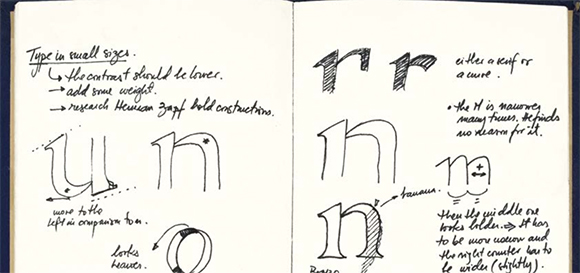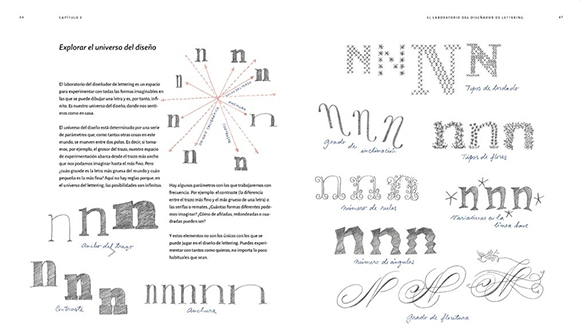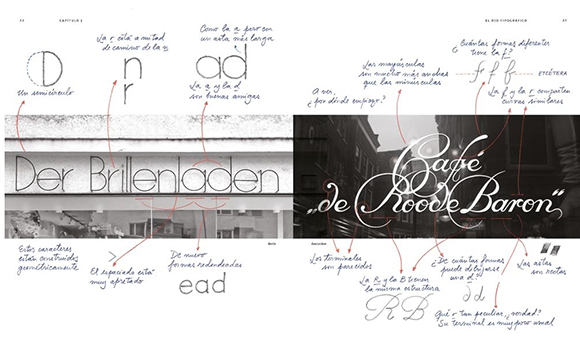
El lettering en su vocablo inglés, o rotulación en español, fue una herramienta importante de la gráfica aplicada que vivió su periodo de esplendor hasta mediados del siglo pasado en el que poco a poco fue sustituido por el vinilo y las tipografías digitales. Pero como al final “todo vuelve”, de un tiempo a esta parte todos los que nos interesamos por la letra y sus formas hemos comprobado el auge que ha experimentado la caligrafía y la rotulación tanto como medio de expresión personal como de desempeño profesional.
Y un buen ejemplo de ello es el libro que hoy comentamos: Los grandes secretos del lettering de la diseñadora e ilustradora Martina Flor. Tengo que reconocer que se trata de un manual ambicioso ya que abarca desde los principios y técnicas en los que se basa este arte hasta el aprovechamiento comercial y profesional del mismo con un capítulo dedicado a la digitalización de la obra para su reproducción comercial y otro en el que la autora ilustra a los lectores sobre la planificación del proyecto y al trato con el posible cliente.
No cabe duda de que adquirir destreza dibujando letras no es tarea fácil por eso me parecen muy interesantes los capítulos destinados a educar el «ojo tipográfico», el que nos muestra los fundamentos de construcción de las letras, y el que repasa los diferentes estilos que las letras pueden adoptar. Saber encontrar los elementos claves de las letras que dan carácter u originalidad a una composición es un primer paso importante para dimensionar las posibilidades que nos ofrece esta herramienta gráfica. Si a ello añadimos el valor del espacio en la construcción y del ritmo y la proporción en la composición seguro que los lectores podrán obtener un conjunto de habilidades que les serán muy de utilidad a la hora de dar forma y sentido a sus primeras incursiones dibujando letras. En las páginas del libro también podemos encontrar las distintas herramientas básicas de escritura que podemos utilizar y el efecto que estas tienen sobre los trazos generados. Además de la breve explicación de las mismas estas se acompañan de varios modelos caligráficos para poder practicar
En general, me gusta del libro su maqueta desenfadada y la utilización profusa de los dibujos de la autora para ilustrar conceptos y técnicas. Esto hace que unos contenidos que en algún caso podrían resultar un tanto arduos sean fáciles de entender y abordar por cualquier tipo de público. Como guinda destacar el prefacio de un gran maestro de la caligrafía y el lettering como es nuestro admirado Ricardo Rousselot.
Los grandes secretos del lettering
por Martina Flor